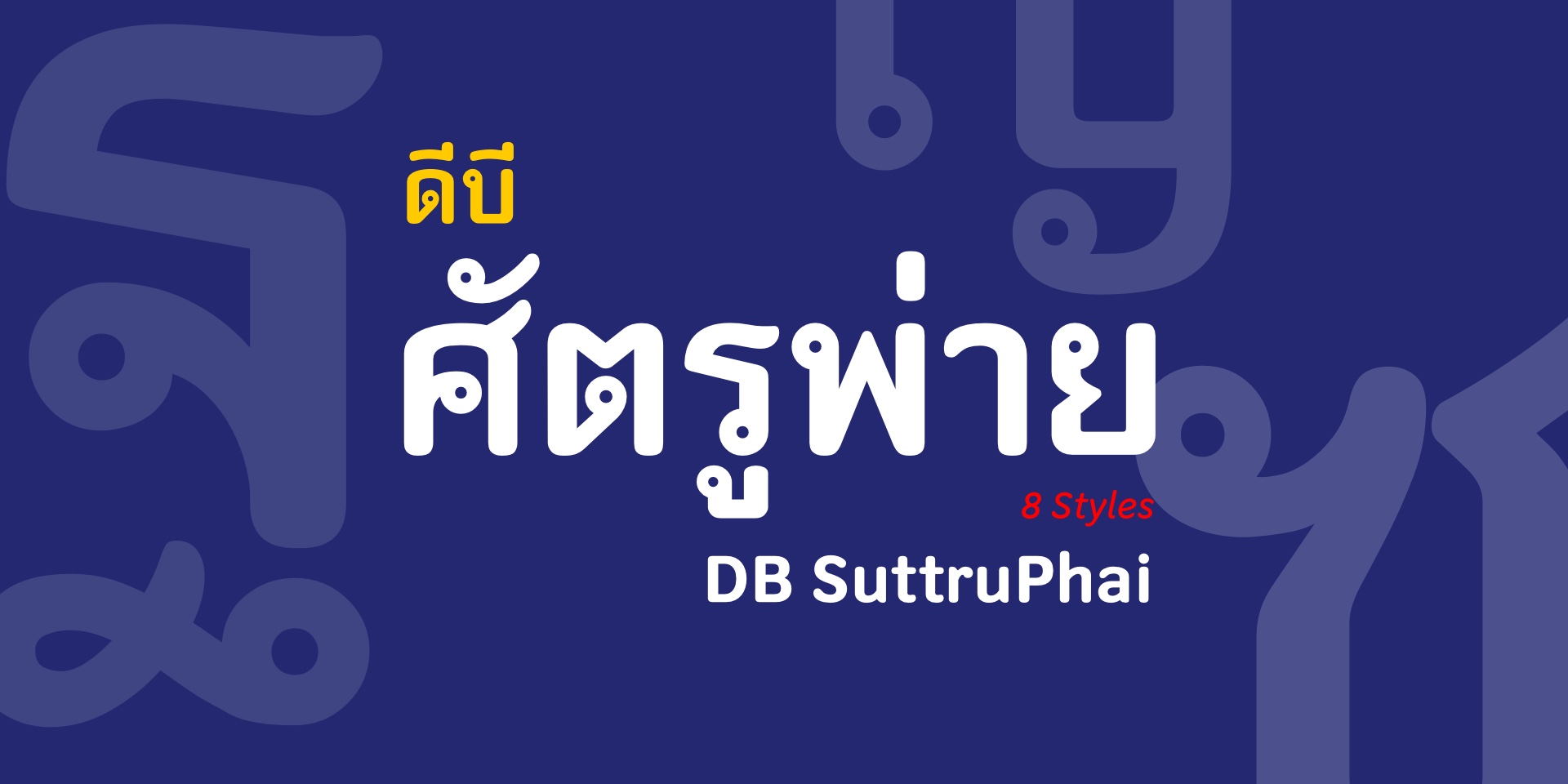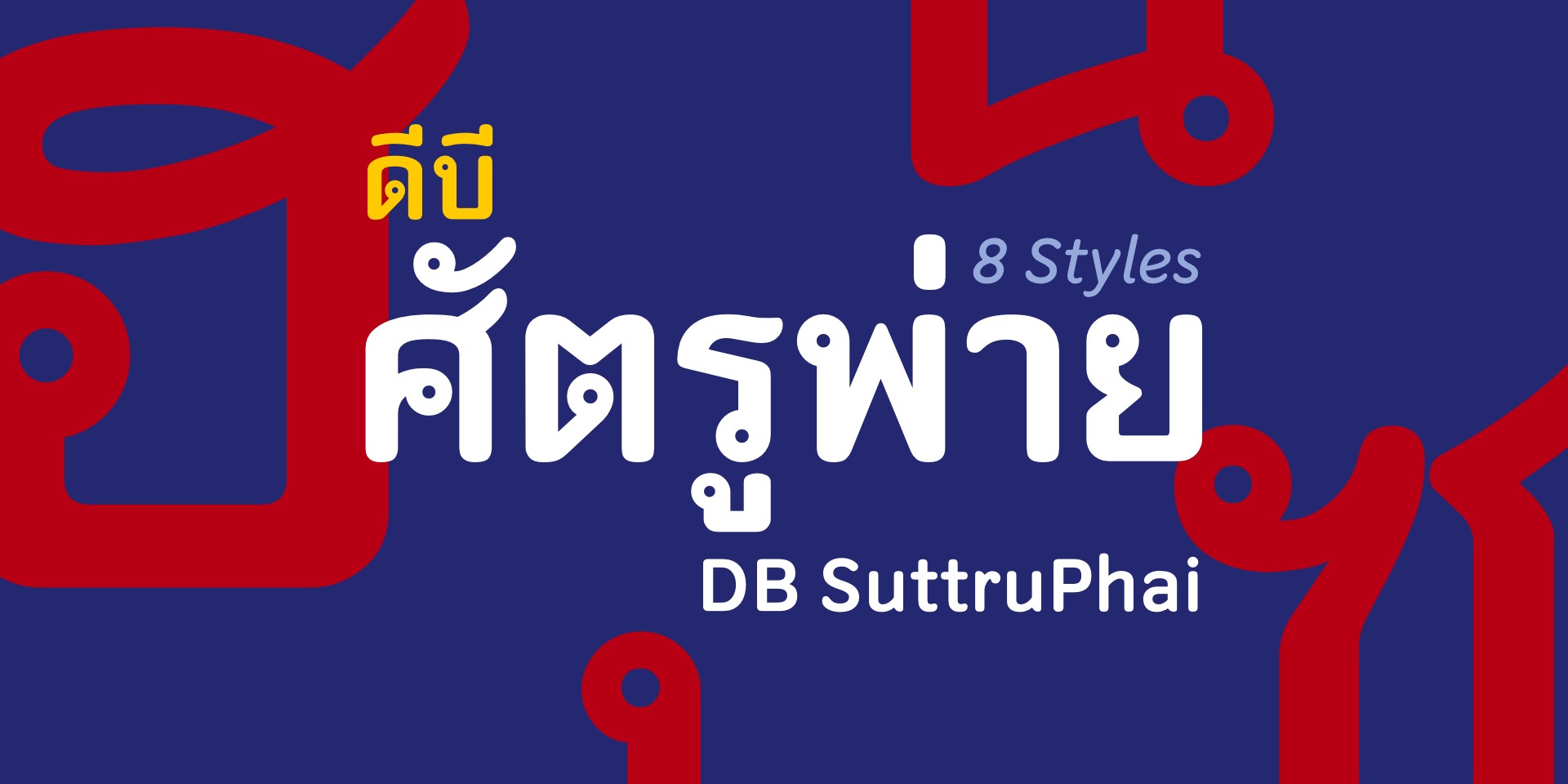
DB SuttruPhai
ดีบี ศัตรูพ่าย
ศัตรูของชาติพ่าย
คู่แข่งของคุณแพ้!
- สถานการณ์สงครามไทย-เขมร ทำให้นึกถึง “ป้อมปราบศัตรูพ่าย”
- แม้ว่าไม่เหลือป้อมให้เห็นแล้ว แต่ชื่อที่เป็นมงคลยังคงอยู่เป็นชื่อเขตจนถึงปัจจุบัน
- ป้อมปราการเดิมทำด้วยอิฐปูน ทำให้จินตนาการถึงอักษรปูนปั้น
- เส้นอักษรต้องไม่บางเกินและปลายเส้นอักษรต้องมนตามข้อจำกัดของงานปูนปั้น
- เลือกอักษรไทยมาตรฐานหัวกลมเพื่อสื่อชัดความเป็นไทย
- หัวอักษรตั้งใจให้เล็กกลืนไปกับความหนาเส้นอักษร เพราะวางเป้าหมายเป็นตัวอวด (display type)
- ฐานอักษรใช้เส้นตรงเพื่อเน้นย้ำความมั่นคงเข้มแข็ง (ดูเส้นฐานล่าง ข, ช, บ, ย, อ) แต่ในชุดตัวเอนเปลี่ยนฐานเป็นเส้นโค้งให้กลมกลืนกับอักษรละติน
- หางอักษรซ่อนลักษณะปลายดาบ (ช, ศ) ของ้าว (ว, อ, า)
- ไม่ยึดติดกรอบขนบ ทำการปรับเปลี่ยนคู่อักษรคล้าย (เช่น ด-ต, ช-ซ) ไม่ให้ดูสับสนเพื่อให้คนไทยสื่อสารกันได้แม่นยำเป็นหนึ่งเดียว
- อ่านง่ายเพียงพอที่จะใช้เป็นตัวอ่าน (text type) ขนาดจิ๋วบนมือถือ
- ใช้ทั้ง 4 น้ำหนักรวมกันเราอยู่
- ศัตรูของชาติพ่าย คู่แข่งของคุณแพ้!